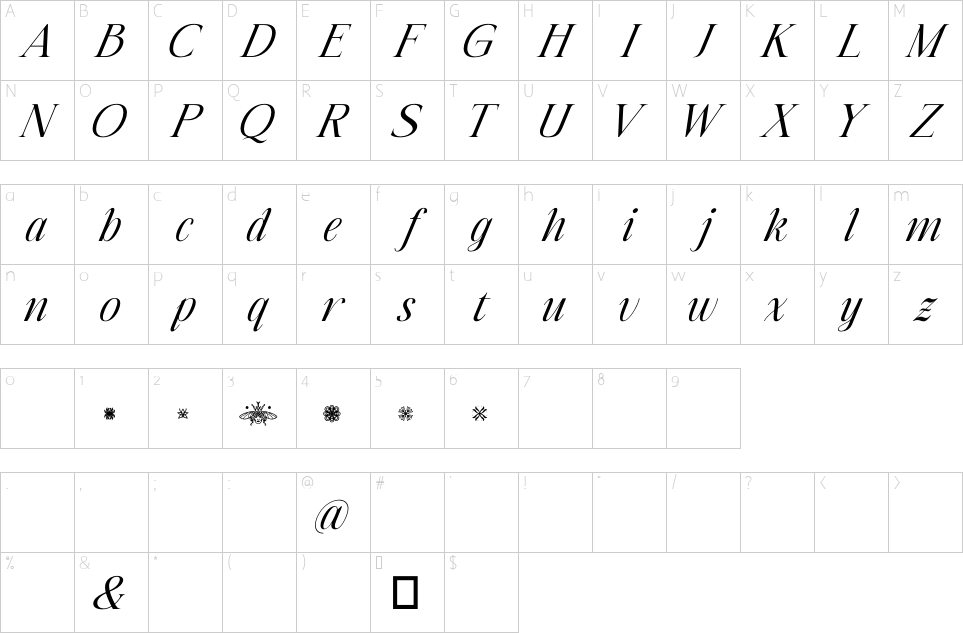
Mapalie é uma fonte grata que oferece um visual agradável e suave, perfeitamente adequada para criações de design gráfico. Sua simplicidade e elegância fazem dela uma ótima opção para aplicativos web, design de sites ou até mesmo para criação de materiais gráficos para redes sociais. Ela foi projetada por um designer não identificado, e já foi baixada pelo menos 493 vezes. Seja você designer de sites, ilustrador ou designer gráfico, Mapalie trará um toque especial a seus projetos. Se você está procurando por uma fonte de alta qualidade que não tenha custos, Mapalie é uma ótima escolha.